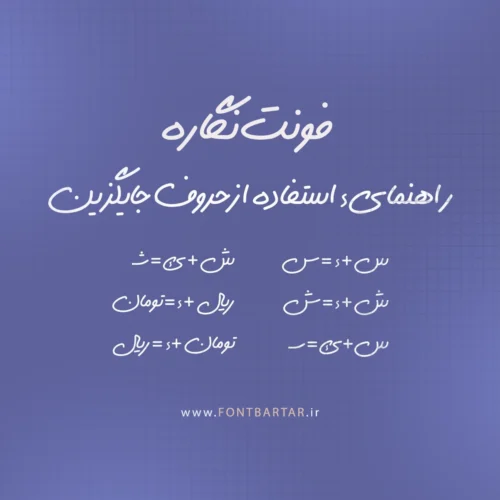
فونت دستنویس نگاره بر پایه یک فونت دستنویس قدیمی و خاطره انگیز بازطراحی و توسط فونت برتر توسعه داده شده است ، در طراحی این فونت دست نویس سعی شده است تمام نواقصی که در فونت مادر خود وجود داشته برطرف گردد و یک فونت دلنشین تر و جذاب تر بوجود آید. استفاده از این فونت باعث میشود خاطرات شیرین گذشته برای شما یادآوری شود.
چرا فونت دستنویس نگاره؟
- فونت دستنویس رایگان نگاره دارای حروف انگلیسی متناسب میباشد .
- به کارگیری کلمه تومان و ریال که در صورت نیاز براحتی می توانید با کلیدهای ترکیبی آنرا فعال نمایید.
- در قلم فارسی نگاره سیلابهای جایگزین اتوماتیک فراوانی وجود دارد که باعث می شود متن شما زیباتر و خواناتر بشه .
- در تایپ فیس فارسی نگاره حروف (س) و (ش) کشیده بصورت جایگزین قرار داده شده است .
- فونت دستنویس آنلاین یک فونت هوشمند، پویا و خاطره انگیز است.
- فونت دستنویس فانتزی پشتیبانی از زبان کردی با نصب کیبورد مخصوص
- فونت دست نویس نگاره اعراب گذاری هوشمند برای هر حرف و کرنینگ متعادل
کجا میتونم از فونت دستنویس نگاره استفاده کنم؟
- در خلق و طراحی استوری ،کاور پستهای شبکه های اجتماعی، پست های خبری ، آموزشی ،عاشقانه ، فانتزی ، کیوت و دپ
- توضیح و شرح عناوین اصلی آثار هنری
- شعار و اعلان های تبلیغاتی
- متون و نوشته هایی که نیاز به شکل و فرمی متفاوت دارن
- عکسنوشته احساسی ، رمانتیک ، عاشقانه ، دپ و کیوت استفاده نمایید.